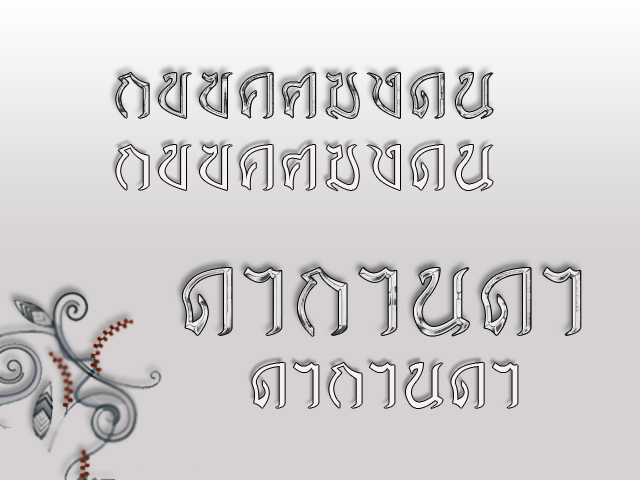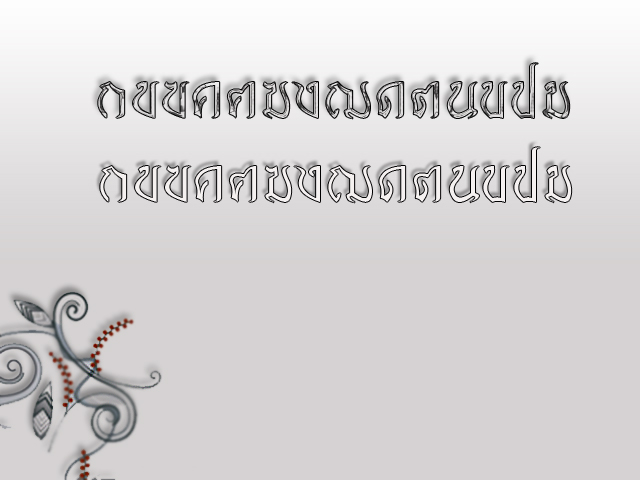
มือใหม่หัดทำฟร้อน
เอามาลงเพิ่มครับ
ทำเก่งจังทำได้ไงคับแถมยังเขียนสวยด้วย
ผมอยากทำเป็นบ้างคับทำไงเหรอคับ :09:
เจ่งจังเลยและสวยด้วย :42:อยากคุยกับนายจังคับจะถามเรื่องทำฟอนต์อะคับ
ได้เพิ่มอีกตัว 2 ตัว  :40:
มีฟอนต์ใหม่ๆ ใช้เยอะๆ
ขอแบบไม่ใส่เอฟเฟคได้มั้ยครับ ผมว่ามันดูไม่อิสระดูเหมือนฟ้อนต์ถูกขังมากไป ยืดหยุ่นในการออกแบบไม่ได้
สวยดีครับ :12: